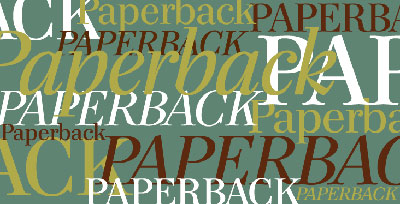
House Industries kündigt »Paperback« anEine wunderschöne neue Schrift von John Downer: Paperback. Gezeichnet
für verschiedene Punktgrößen (Texte: 6, 9 und 12 pt; Headline:
48 und 96 pt), mit einer charmanten Kursiven, Zierbuchstaben, Symbolen und
ausgeklügelten OpenType-Features. Lesen Sie mehr über die Vorzüge
der Schrift und ihre nicht ganz jugendfreie Entstehungsgeschichte im
Sündenbabel Las
Vegas.
![]() Alle Abbildungen: House Industries Mit zunehmender Größe der Paperback-Matrizen (6, 9 und 12
Punkt für Texte, sowie 48- und 96 Punkt für Headlines) verfeinern sich
Strichstärke und ihre »typografische Farbe«: die Konturen werden
glatter, die Serifen feiner. Die folgende Animation zeigt die Änderungen,
beginnend von der Headline-Version bis hinunter zur
6-Punkt-Textvariante:
![]() Die einzelnen Buchstabenformen bieten ausgeklügelte Details, die eine exzellente Lesbarkeit auch in kleinen Druckgrößen garantieren. Diese Feinheiten sind es, die Paperback-Texten eine einzigartige »Maserung« geben, die sich über alle Schnitte und Stile erstreckt. Die Text-Version der Familie bietet mehrere Ziffernarten, darunter Mediäval-, Tabellen- und zugerichtete Versalziffern; Bruchziffern liegen ebenfalls in zwei Varianten vor. OpenType-fähige Programmen bauen die Brüche automatisch zusammen. ![]() 25 dekorative Symbole für Rahmen und Muster runden den Zeichenvorrat von Paperback ab. Hinzu kommt ein kompletter Vorrat an Akzentbuchstaben, so dass sich mit Paperback über 25 Sprachen setzen lassen. ![]() Originalton House Industries zu Paperback: Die rohe Kreativkraft, die John Downers Wirken steuert, verfeinerte sich zu einer behutsame Note und mündete in eine meisterliche Schriftfamilie. Sogar in kleinen Größen und unter schwierigsten Bedingungen entfaltet Paperback Kraft und eine unvergleichliche Lesbarkeit. Holzfasern, ein High-Speed-Internetseitenaufbau, schlafende Drucker, launische Pixel sind kein Hindernis für die robusten Formen eines jeden Paperback-Schnittes. Von bombastischen Großflächenplakaten bis zum winzigsten Hinweis ... Paperback garantiert stets wohltemperierte Typografie. ![]() Die aufregende Geschichte der Paperback (nach www.houseindustries.com Gleichermaßen herzerfrischend wie herzzerreißend ist die Geschichte eines Schildermalers aus dem flachen Iowa, der sich von der schillernden Sündhaftigkeit Las Vegas’ locken ließ, um dort mit seinem Talent schnelles Geld zu verdienen. Er ahnte nicht, dass ihn eine unerschöpfliche Lasterhöhle geriet, wo die Begierde exotischer Tänzerinnen keinen Halt mehr kennt beim Anblick gewölbter Muskeln, die sich über Jahre durch Kornschaufeln und Heuballenstapeln entwickelt hatten. Es dauerte nicht lange bis die wollüstigen Dirnen noch ganz andere vorstehende Teile an ihrer Beute entdeckten. Als sein Bedarf durch die gierigen Sirenen gesättigt war, fand unser junger Held Gefallen an einem neuen Ziel, das ihn auf eine ehrgeizige typografische Eroberung lockte ... wir kennen es heute als »Paperback«. ![]() Alle Abbildungen: House Industries Paperback gibt es bei FontShop in zwei Paketen (Text, Display), beide gemeinsam mit Preisvorteil; allerdings nicht im Download sondern nur per Post – damit Sie in den Genuss der liebevollen House-Industries-Verpackungen kommen. Herausgegeben: Do - Mai 12, 2005 at 12:24 nachm. | |